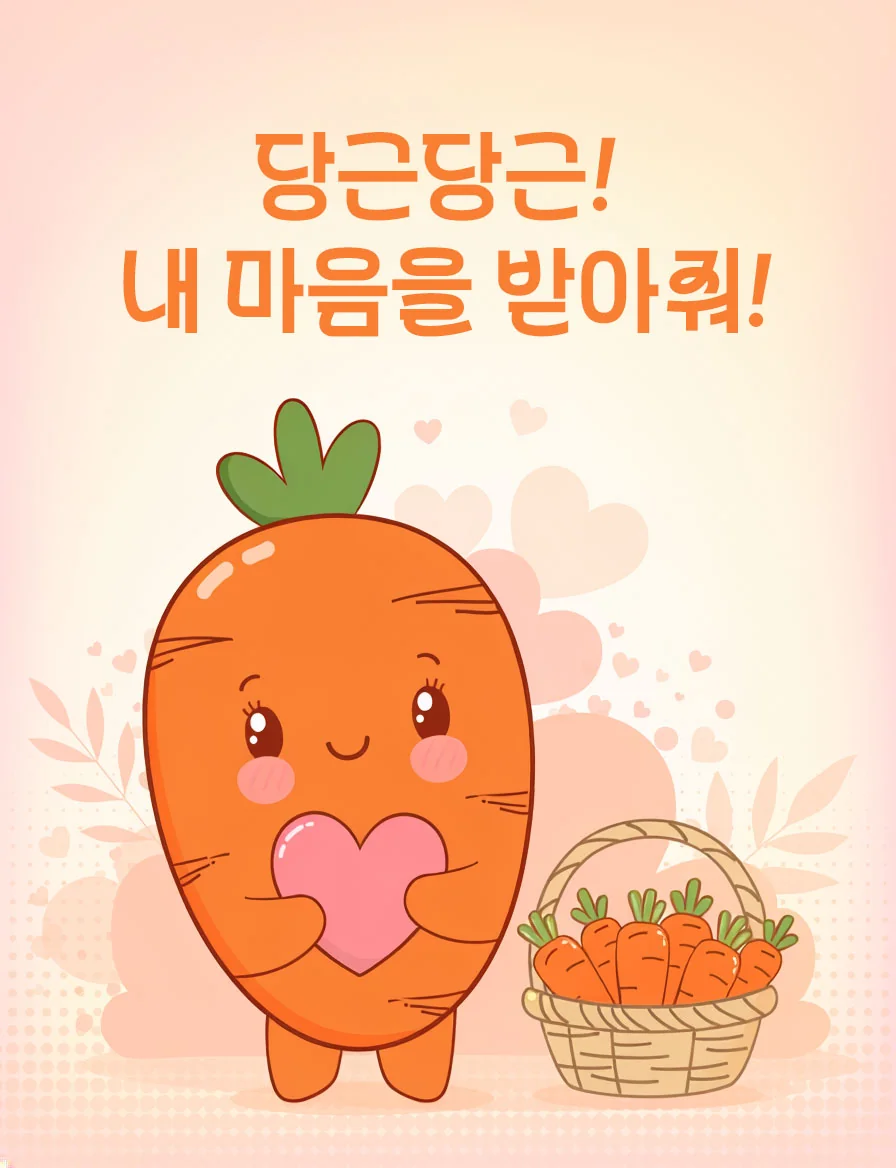
HS산토끼체2.0 — 토끼네활자공장에서 배포하는 무료 폰트입니다. 상하가 비대칭인 사다리꼴 구조와 꼬인 듯한 글자가 개성을 만드는 장식체
토끼네활자공장이 2024년에 내놓은 서체로, 2022년에 나온 1세대의 후속작입니다. 이 파운드리에서 2.0은 개선판이 아니라 별개의 디자인이라는 뜻입니다.
두 세대의 제작 방식이 극과 극입니다. 제작자는 1세대를 하루 만에 완성했다고 회고하면서, 이번에는 1년이 넘게 걸렸고 열네 번이나 디자인을 갈아엎은 뒤 열다섯 번째에야 마무리할 수 있었다고 밝혔습니다. 그러면서 내린 결론이 효율성보다 설득력 있는 완성도가 더 중요하다는 것이었습니다.
세대를 잇는 방식도 직접 설명했습니다. 2세대는 1세대와 디자인이 완전히 달라졌지만 시옷 계열의 리본 디자인은 계승했다는 것입니다. 파일에서 재어 보면 낱자가 폭보다 높이가 커서 세로로 서 있고, 자면을 꽤 채워 인상이 또렷합니다.
굵기는 Bold 하나입니다. 한글은 2,498자로 1세대보다 오히려 줄었는데, 제작자가 전혀 필요 없을 것 같은 284자를 덜어냈다고 밝혔습니다. 그만큼 드문 음절은 빠지니 정해진 문구에만 쓰세요. 개인과 상업 모두 무료이고 수정과 재배포까지 자유롭지만 폰트 파일 판매는 금지됩니다.